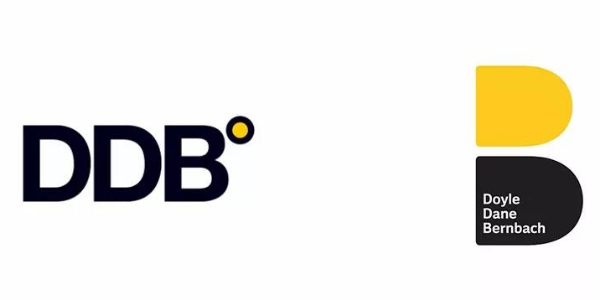
世界顶级4A公司换LOGO,原来改回第一稿, 不是梦
DDB,恒美广告公司,世界顶级4A广告公司,在世界96个国家有206个办事处,到现在已经有70年的历史了。
在70年期间,DDB服务了很多知名品牌,大众,保时捷,宾利,麦当劳,联合利华,百事可乐,百威,强生,佳得乐等都是DDB的忠实客户。
DDB的名字由来是由3位创始人Bernbach , Doyle , Dane 首字母组成的,两个大写的字母D组成一个字母B,形成了恒美广告公司最早期的LOGO。近日DDB为庆生发布了全新的品牌形象,新LOGO设计基于70年前LOGO而诞生的。
创始人Bernbach , Doyle , Dane
最早期的恒美广告公司LOGO
70年前LOGO草稿
70年前可以做出这样简洁的设计实属不易,这次全新的LOGO,保留了两个D组成B的设计思路,对标志进行了优化。网友:“改回第一版魔咒,70年长期有效”。
DDB新标志与上一版本对比
新版本的LOGO,上下两个D变成了实心的,一个黄色,一个深灰色,3位创始人的名字写在了灰色D上,两个字母D的大小也做了区别,上小下大。
因为整体太像字母B了,也有人觉得,这个LOGO不像以前可以看出DDB,现在只能看出B了..
不过小编觉得,这个不是问题的重点,从个人经验来看,这个LOGO的造型相对平淡,比较容易出现雷同的情况,虽然好像大公司都不是很在乎“撞车”。
上一个让人印象深刻的广告公司LOGO焕新应该要数奥美了,同样是70周年,不同的是,奥美发布的全新LOGO,彻底取代了创始人的手写体,而DDB却是改回第一稿。
来欣赏一下DDB的视觉延展